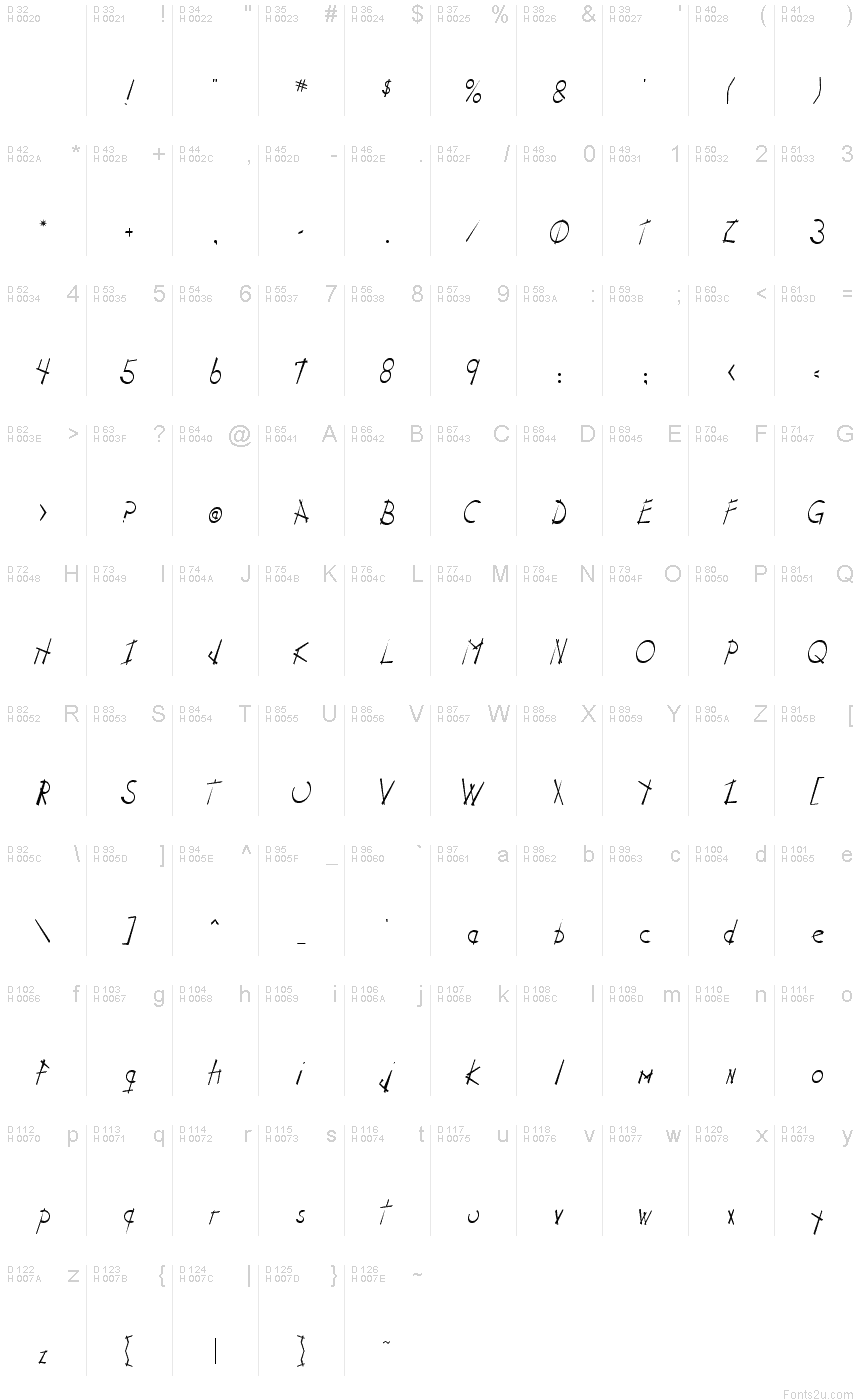
Stix n Stonz من تصميم R.Gast من GreyWolf WebWorks هو خط مجاني مكتوب بخط اليد يتميز بمظهر مرح يشبه الأغصان والحجارة. تبدو الحروف وكأنها ارتجالية، ناتجة عن ضربات فرشاة سريعة وعلامات مكسرة، حيث تمتزج الخطوط الطويلة مع القطع الحادة التي تشبه الحصى، مما يمنح الخط ككل إيقاعاً خشناً وحرفياً.
هذا يجعله خياراً طبيعياً للمجلات المستقلة، وملصقات فعاليات الأطفال، ومنشورات موسيقى الأندي، وعناوين سجلات القصاصات، ورسومات الشعارات الأولية التي تتطلب لمسة يدوية عفوية بدلاً من المظهر المصقول. استخدمه عندما تريد أن تضفي على العناوين القصيرة أو الأغلفة طاقة محلية الصنع وخامة؛ فالضربات غير المنتظمة هي التي تقوم بمعظم العمل هنا.